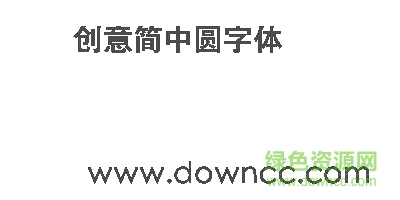
創(chuàng)意簡中圓字體是一款端正大氣的創(chuàng)藝字體,筆畫粗壯,平整順滑,看上去非常美觀,使用字體后會讓你的字形看上去大氣美觀,喜歡就來綠色資源網(wǎng)下載吧!
美工設計方面的字體,該字體渾厚高古,勁健雄奇,意態(tài)跌宕,蒼勁峻逸,看上去十分美觀,整體效果非常統(tǒng)一,且字庫完整,可以廣泛應用于廣告設計、包裝印刷、海報、ppt、影視制作以及內容用字等領域,